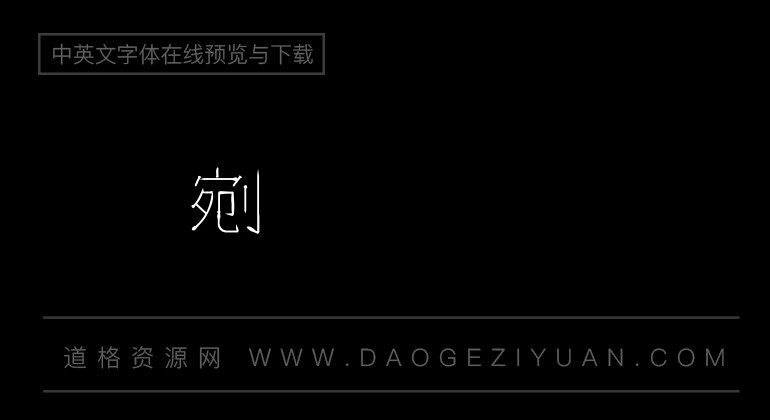
金梅铁钉字体范例
金梅铁钉字体是一种拼音字体,由中国著名的汉字字体设计师张梅设计,是一种简洁、优雅的拼音字体,它的字体特点是每个字母的笔画线条简洁,比较统一,字形较为柔和,没有太多的弯折,比较符合中国书法的风格,同时也适用于英文字体的设计,这种字体适用于各种文字设计,比如文字标识、标牌、海报、画册等。
金梅铁钉字体范例是一款非常不错的手写艺术字体,具有很好的视觉感,适合于文化类的宣传设计、商业类品牌的广告和产品包装设计以及个性化文字排版等较多场景。
金梅铁钉字体范例字符映射图